Điểm danh 5 website tạo font chữ Instagram đẹp, “có gu” không thể bỏ qua
Bạn đang muốn tìm các font chữ Instagram đẹp để trang cá nhân của mình trở nên đẹp và “có gu” hơn thì hãy theo dõi bài viết này, FPT Shop sẽ điểm danh 5 website tạo font chữ Instagram đẹp nhé.
5 website tạo font chữ Instagram đẹp
Font chữ trên tiểu sử Instagram hoặc trên story Instagram của bạn cũng đủ để gây ấn tượng với một ai đó. Tại đây, FPT Shop sẽ bật mí 5 website tạo font chữ Instagram đẹp, có thể dùng cho cả điện thoại và máy tính nhé.
Meta Tags là một nền tảng cung cấp các font chữ đẹp, độc lạ cho mọi người tham khảo và dùng cho Instagram. Đặc điểm tuyệt vời của website này là cho phép người dùng xem trước nội dung mình viết sẽ hiển thị như thế nào trước khi sử dụng nó.
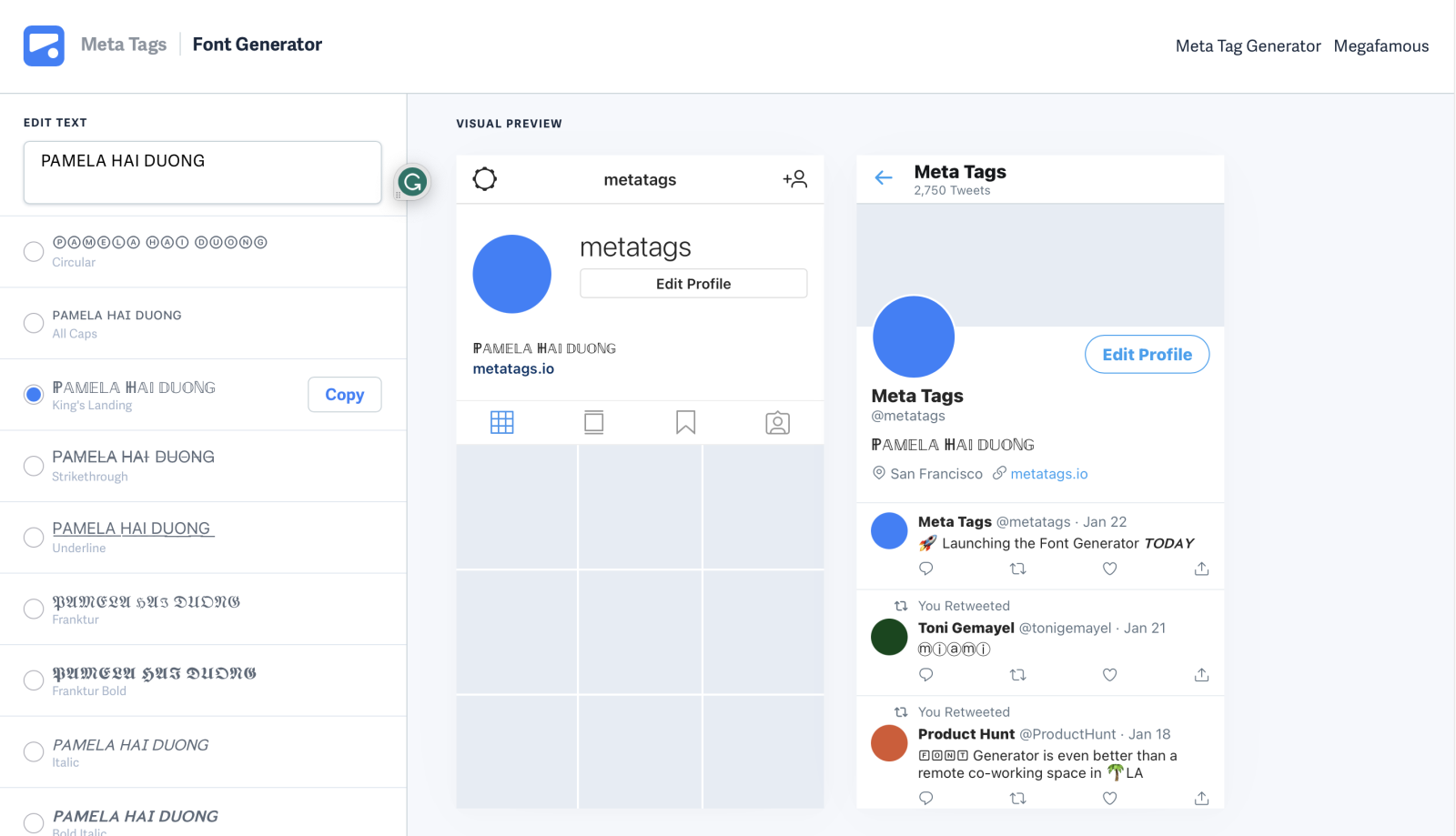
Bạn nhập nội dung vào ô Edit text ở trang chủ của website, ngay khi bạn nhập nội dung thì các font chữ với nội dung tương tự sẽ hiển thị phía bên dưới. Sau đó bạn chỉ cần chọn font chữ mà mình muốn sử dụng bằng cách nhấn Copy rồi Paste vào nơi mà bạn vị trí mà bạn muốn như tiểu sử Instagram, story Instagram,...
Instagram Fonts là một website cung cấp font chữ Instagram đẹp, bạn chỉ cần nhập nội dung vào ô trống ở đầu trang chủ. Ngay khi đó trang web sẽ tự động hiển thị các font chữ với nội dung bạn vừa nhập ở bên dưới. Bạn chỉ cần quan sát và lựa chọn mẫu font chữ mà mình thích nhất rồi chọn copy và paste vào vị trí mà mình muốn trên Instagram.
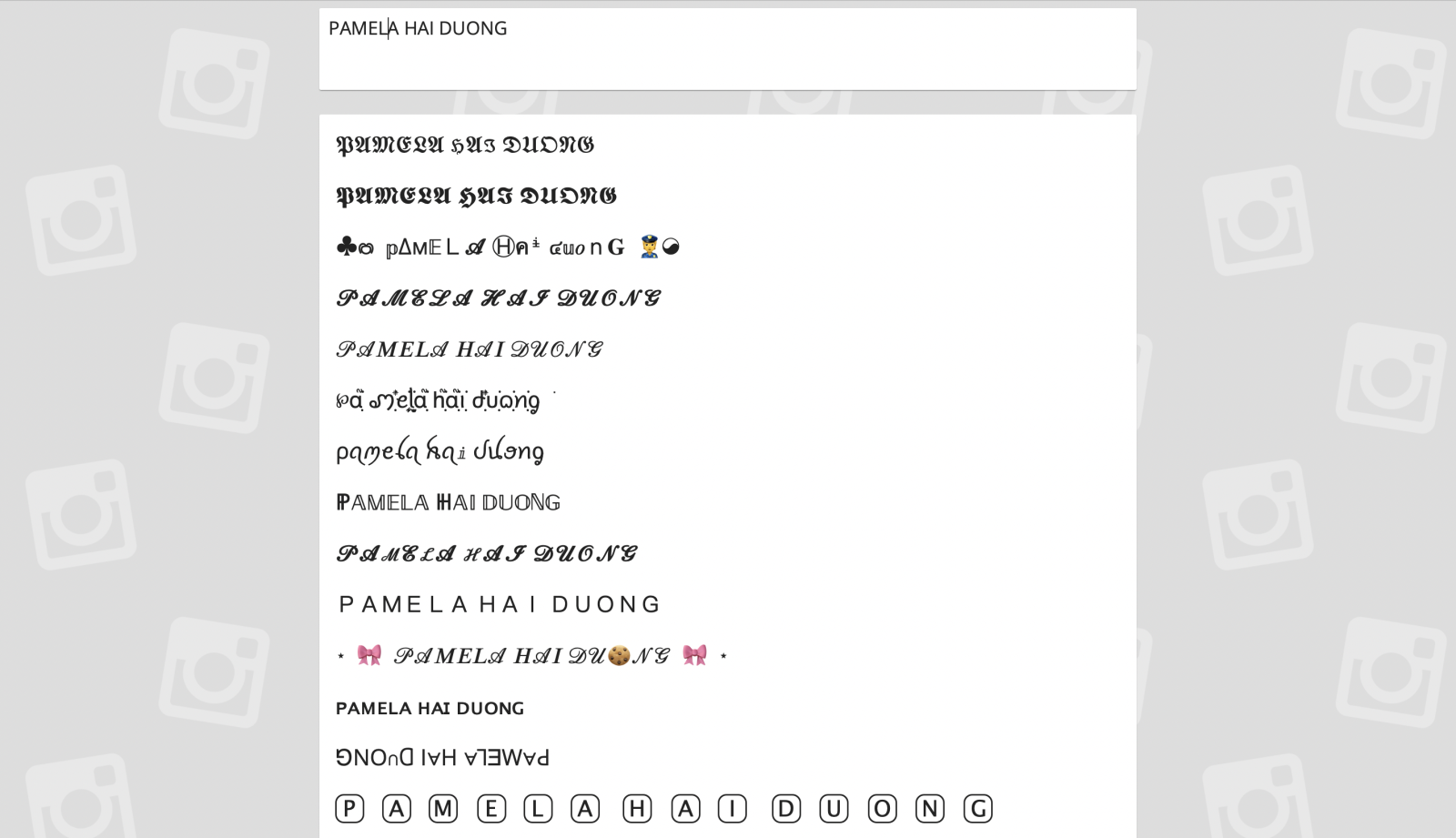
Instagram Fonts sẽ có những kiểu font chữ có cả biểu tượng cảm xúc, cực kỳ dễ thương.
Cách sử dụng của website Instagram Fonts Generator cũng tương tự như Instagram Fonts, đồng thời cũng bao gồm nhiều font chữ có biểu tượng cảm xúc khác nhau. Tuy nhiên, ưu điểm của Instagram Fonts Generator là không xuất hiện nhiều quảng cáo làm gián đoạn quá trình sử dụng của bạn như Instagram Fonts.
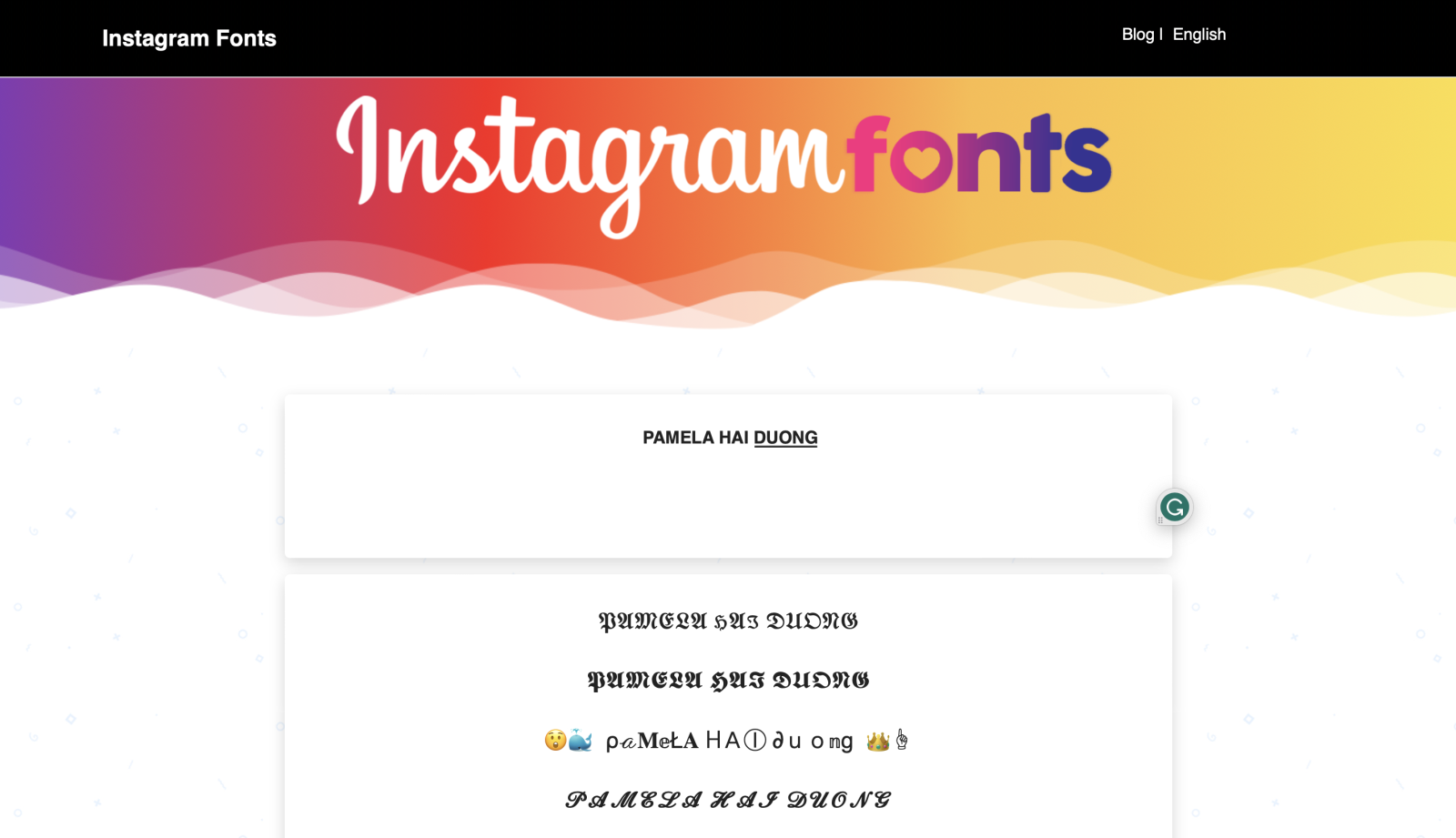
Bạn nhập nội dung cần viết vào ô trống ở giữa màn hình, sau đó website sẽ hiển thị nhiều font chữ với nội dung vừa nhập ở bên dưới cho bạn lựa chọn. Cuối cùng bạn hãy chọn font chữ Instagram đẹp và phù hợp với sở thích nhất rồi nhấn copy và paste vào vị trí mà bạn mong muốn.
Giao diện của website Font for Instagram sẽ có phần khác so với 2 website (Instagram Fonts, Instagram Fonts Generator), ô bên phải là để nhập nội dung mà bạn muốn chia sẻ, còn ô bên phải sẽ hiển thị các mẫu font chữ để bạn lựa chọn.
Font for Instagram cũng sẽ có rất nhiều font chữ mang nhiều phong cách nghệ thuật, kèm theo đó là những biểu tượng cảm xúc siêu dễ thương.
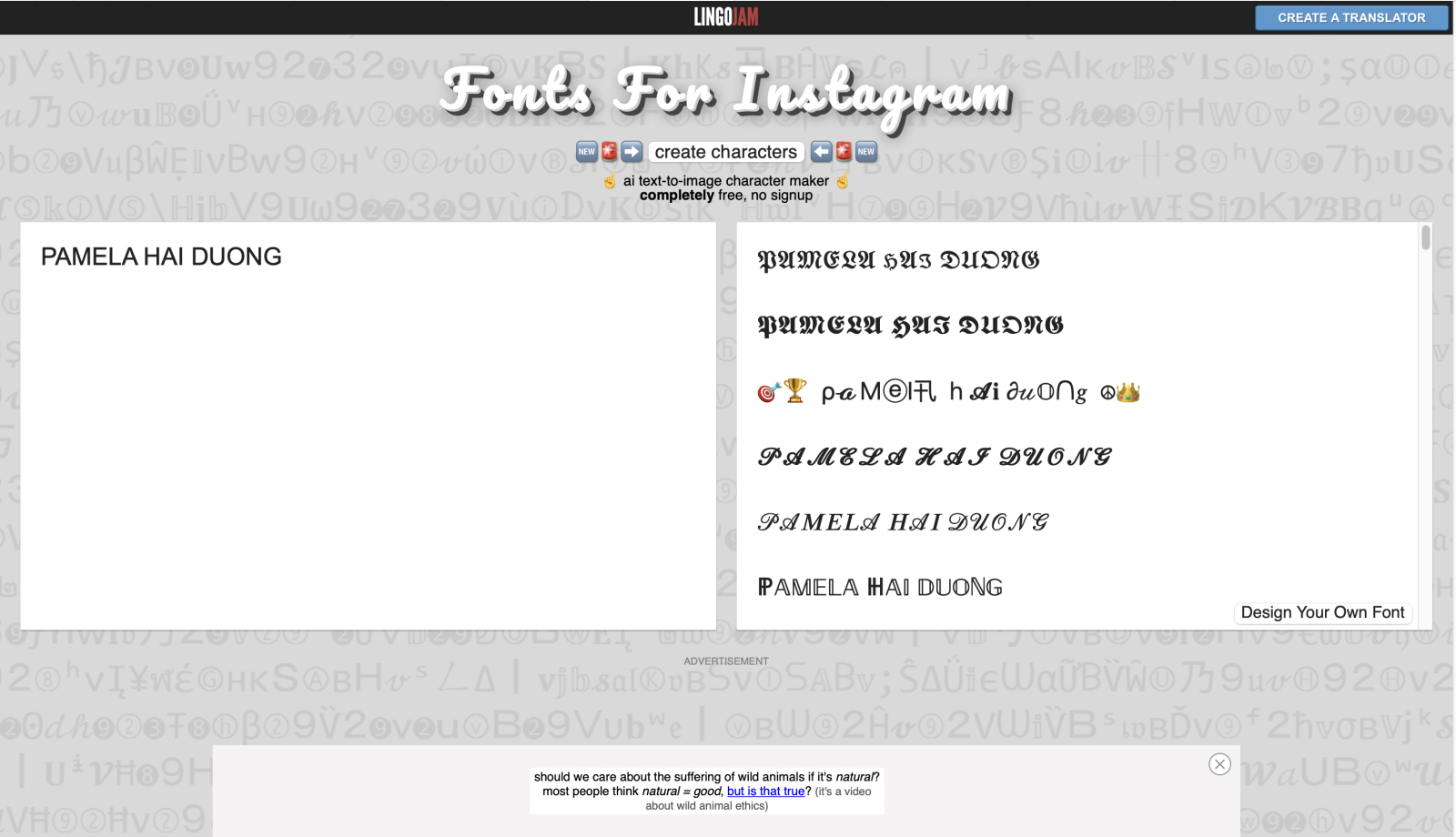
Website cũng rất dễ sử dụng bằng cách nhập nội dung mà bạn muốn chia sẻ vào ô bên trái màn hình, ngay khi đó tại ô bên phải sẽ hiển thị các font chữ với nội dung bạn vừa nhập. Cuối cùng bạn chỉ cần chọn kiểu chữ mà mình thích nhất rồi chọn copy và paste vào vị trí mà mình muốn.
Sprezz Keyboard là một trong những website có nhiều font chữ Instagram đẹp nhất. Để sử dụng, bạn chỉ cần nhập nội dung mà mình muốn vào ô Enter text stylized, các font chữ sẽ hiển thị ở ngay phía bên dưới, bạn chỉ cần lựa chọn font chữ mà bạn thích nhất thôi. Sau đó, bạn bôi đen chữ và chọn copy rồi paste vào vị trí mà mình muốn.